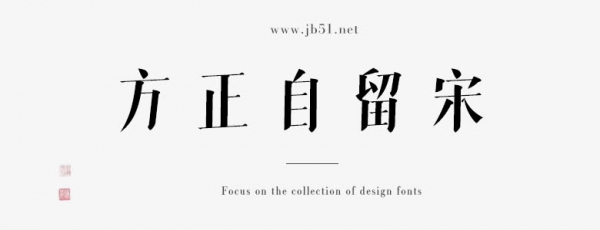
方正自留宋家族由方正字庫(kù)梁標(biāo)設(shè)計(jì)師出品的藝術(shù)字體,字體結(jié)體修長(zhǎng)、重心取高、中宮緊致,氣勢(shì)俊俏挺拔;筆畫(huà)內(nèi)斂富有韌度,適合應(yīng)用于藝術(shù)設(shè)計(jì)、平面宣傳設(shè)計(jì)、網(wǎng)頁(yè)設(shè)計(jì),書(shū)法等領(lǐng)域。
自留宋,字體命名取自唐代王維詩(shī)作《山居秋暝》中「王孫自可留」詩(shī)句而來(lái)。自留宋結(jié)體修長(zhǎng)、重心取高、中宮緊致,氣勢(shì)俊俏挺拔;筆畫(huà)內(nèi)斂富有韌度。整體字態(tài)取法于傳統(tǒng)書(shū)法藝術(shù)險(xiǎn)中求穩(wěn)之體態(tài),其中以收筆為代表,則取法于顏體收筆,含而不發(fā)。擬態(tài)而非求真。起收轉(zhuǎn)運(yùn)對(duì)筆畫(huà)連貫與呼應(yīng)有很好的交代,既汲取了中國(guó)傳統(tǒng)書(shū)法藝術(shù)的書(shū)寫(xiě)性,又賦予了其符合當(dāng)下審美和使用趨勢(shì)的結(jié)構(gòu)和體飾;緊致凝煉而又內(nèi)在飽滿;氣質(zhì)清冷凜冽卻也活力十足。